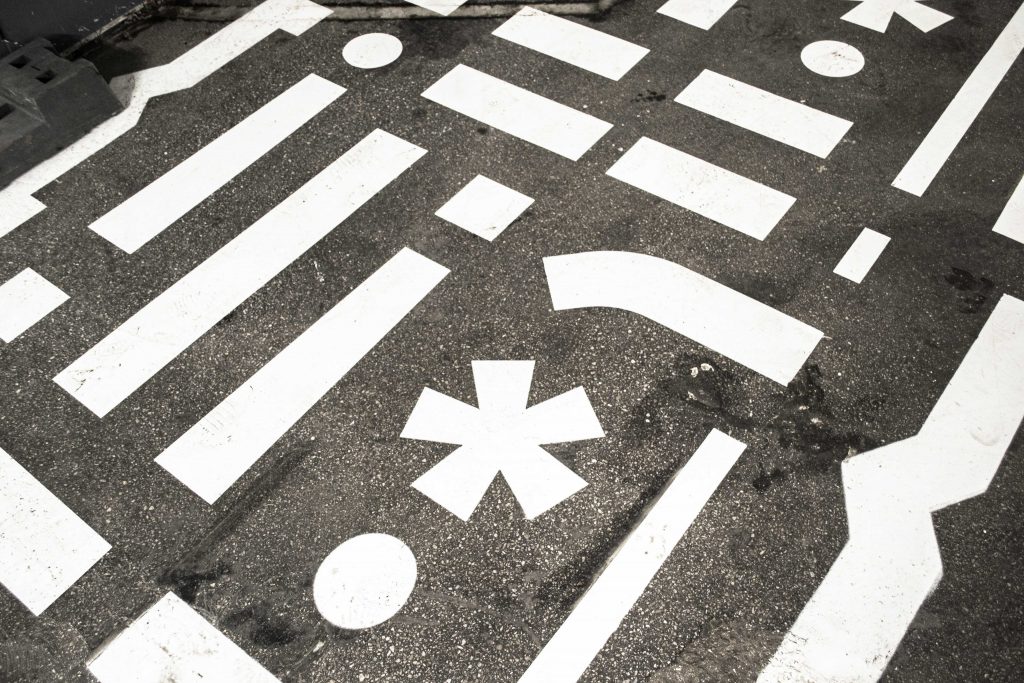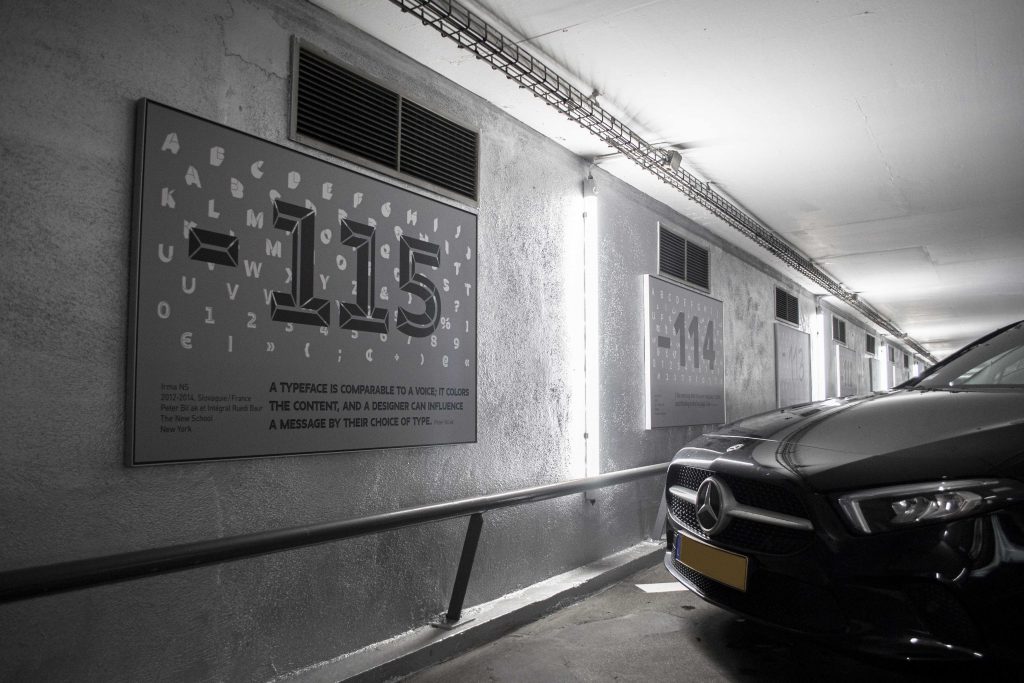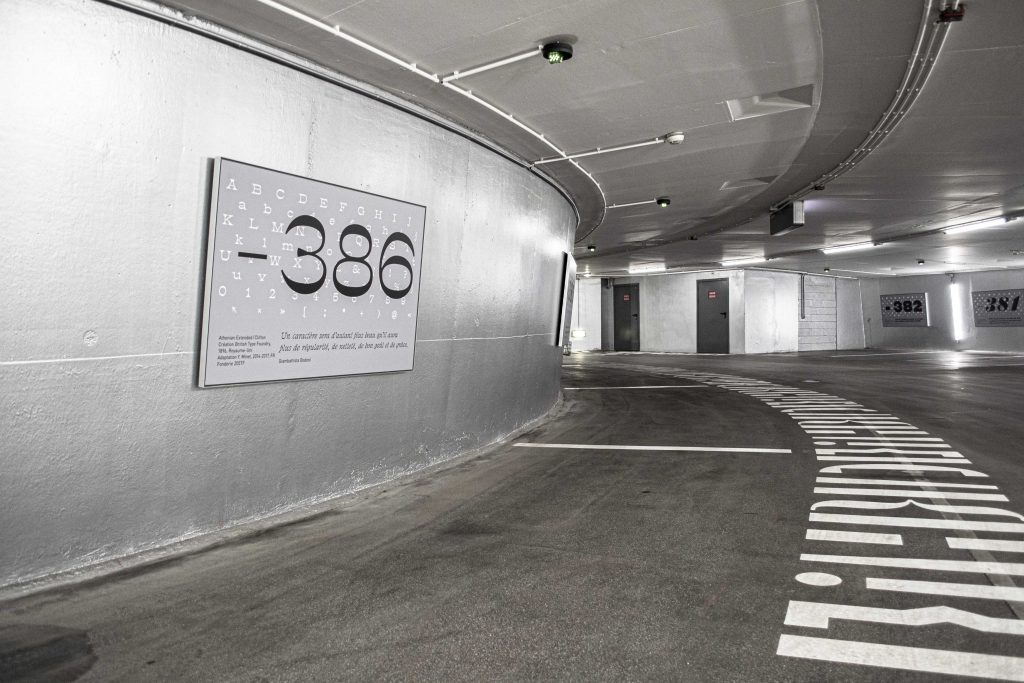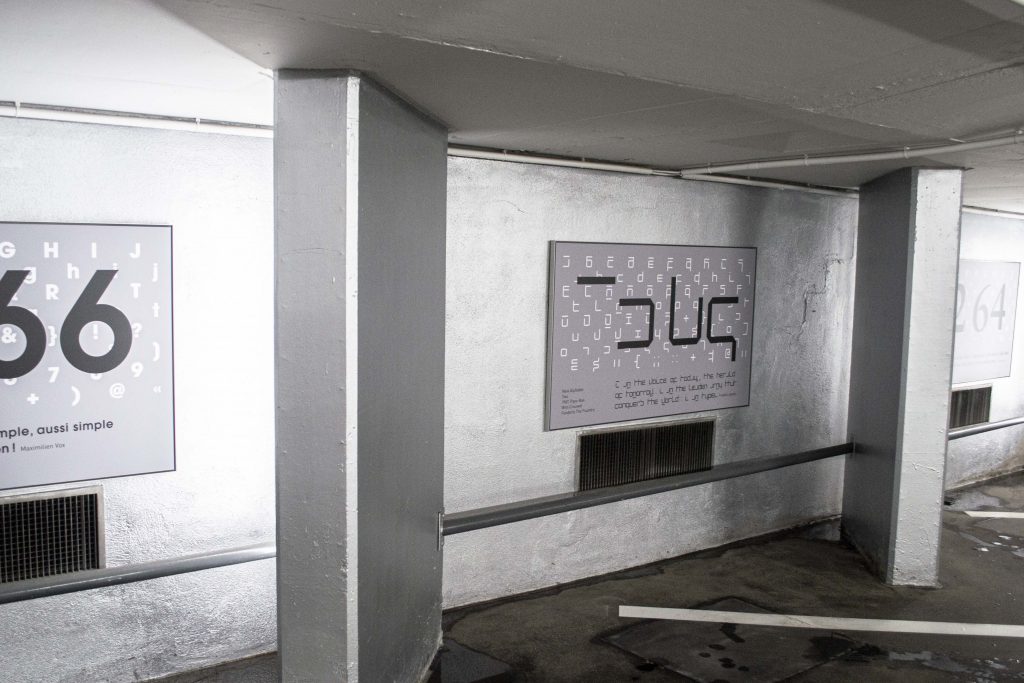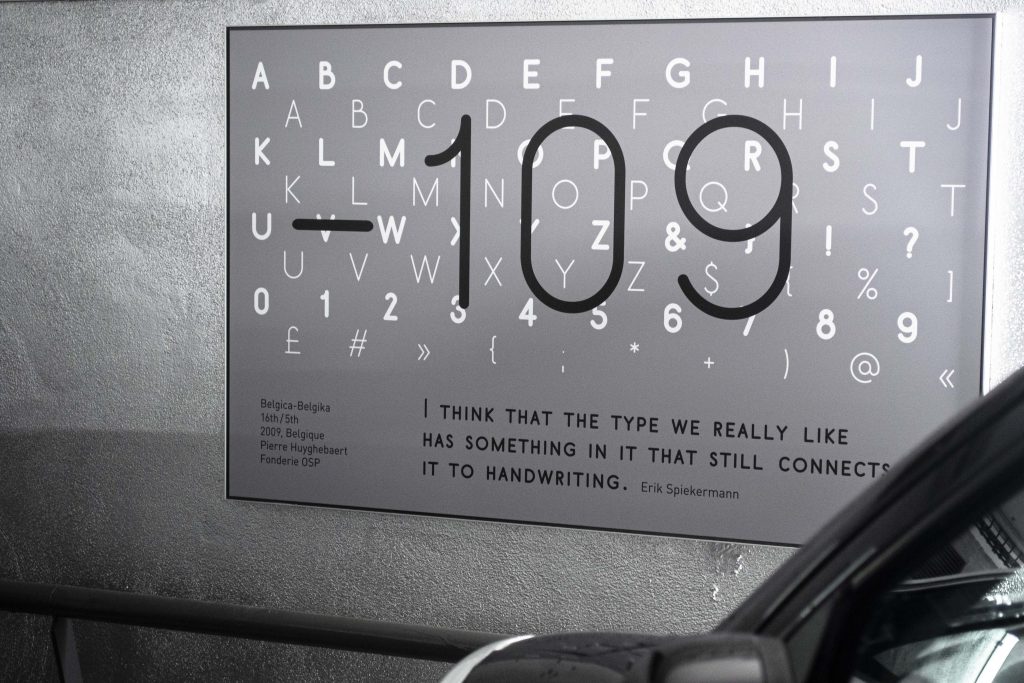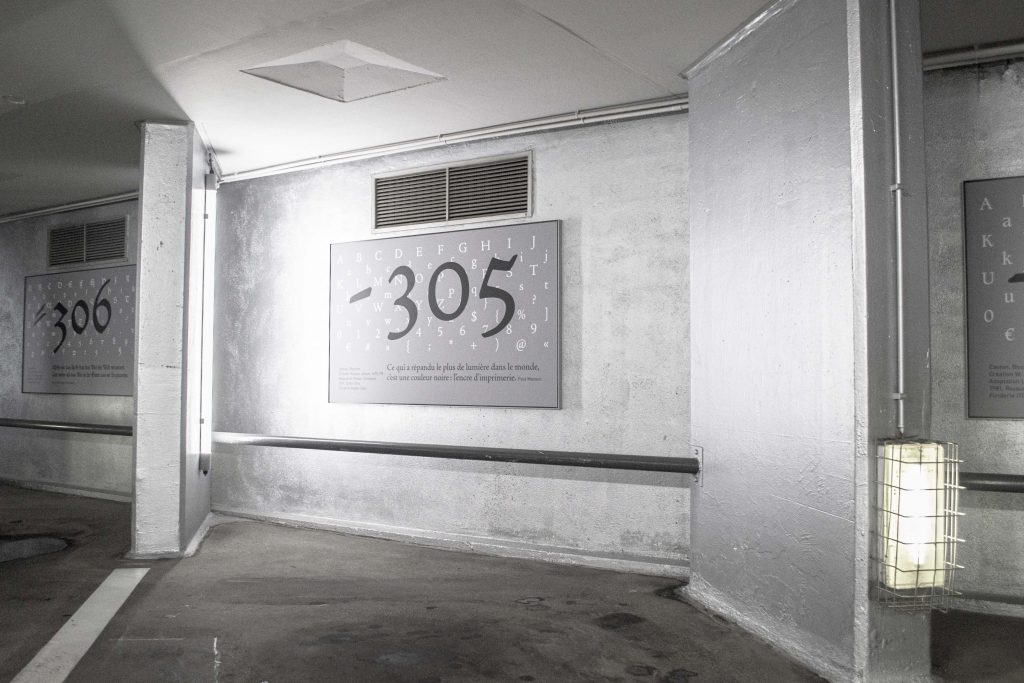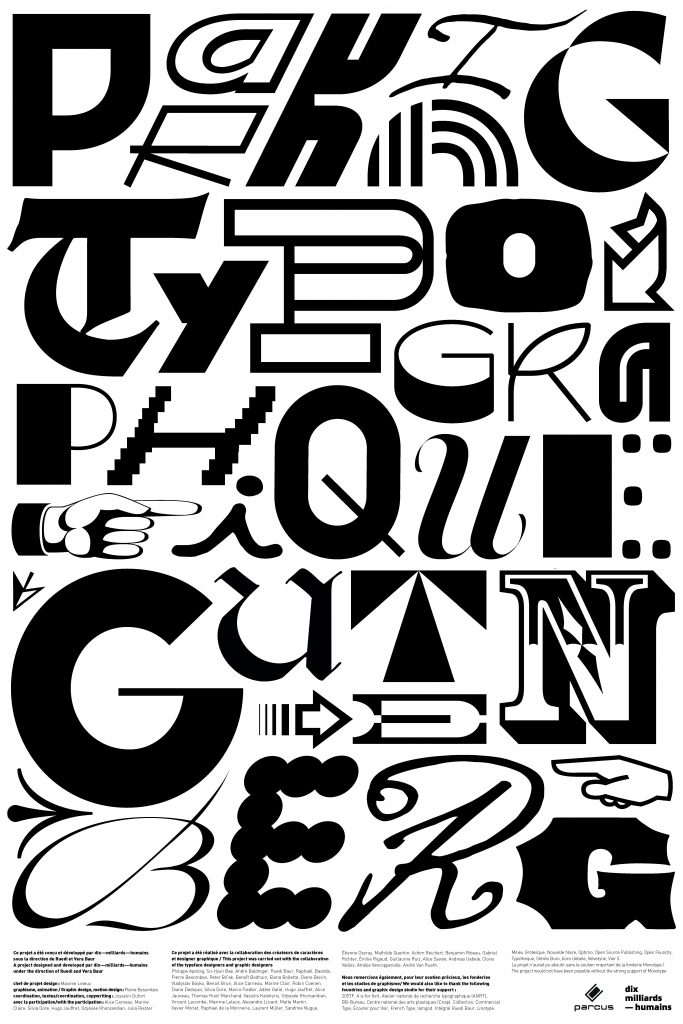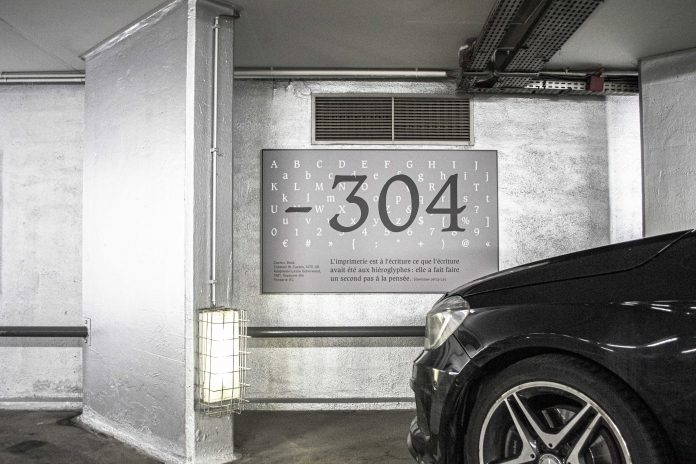
À Strasbourg, dix—milliards—humains décore le parking Gutenberg de plusieurs centaines de typographies
Dix—milliards—humains, atelier de recherche-création, de développement et conseil en design, est spécialisé dans les travaux d’aménagement urbain. Avec à sa tête Ruedi et Vera Baur, l’atelier mêle les approches de sociologues, d’urbanistes, d’architectes, de paysagistes et de designers dans une perspective transdisciplinaire. Dix—milliards—humains s’est récemment penché sur la question des nouveaux usages des parkings de centre-villes avec le cas du parking typographique Gutenberg à Strasbourg. Tout en rendant hommage à l’inventeur de l’imprimerie, les designers y ont créé un parcours à la fois narratif et fonctionnel.
Les structures labyrinthiques des parkings impliquent une signalétique claire et bien ajustée. Numéro de place, d’étage, sens de circulation ou sorties, elle doit guider le plus naturellement possible des utilisateurs bien souvent désorientés. Dans le cas du parking Gutenberg, les designers de dix—milliards—humains ont choisi de remplacer les signes utilisés habituellement dans ces espaces par des caractères de notre alphabet. Dès son entrée dans le parking, le piéton est guidé vers l’ascenseur par un tapis de virgules et de points d’exclamation assemblés, avant d’être accueilli par un couple de parenthèses lui permettant d’entrer dans l’ascenseur. Chaque place de parking met également en avant une police différente. Un panneau indique le numéro de place et fait apparaitre l’histoire de cette police, le nom de son créateur et la fonderie qui la commercialise. Au niveau -1, ce sont les travaux de créateurs, d’étudiants et de professionnels contemporains qui sont exposés, témoignant par la même occasion de la vivacité actuelle du domaine. Les niveaux -2 et -3 montrent quand à eux des polices de caractères créées entre le 15e et le 20e siècle, ainsi que des typographies réalisées par Gutenberg lui même.
Tout en conservant sa fonction première d’espace de stationnement, le parking Gutenberg revêt désormais une dimension culturelle et pédagogique, permettant de découvrir la typographie et son histoire.